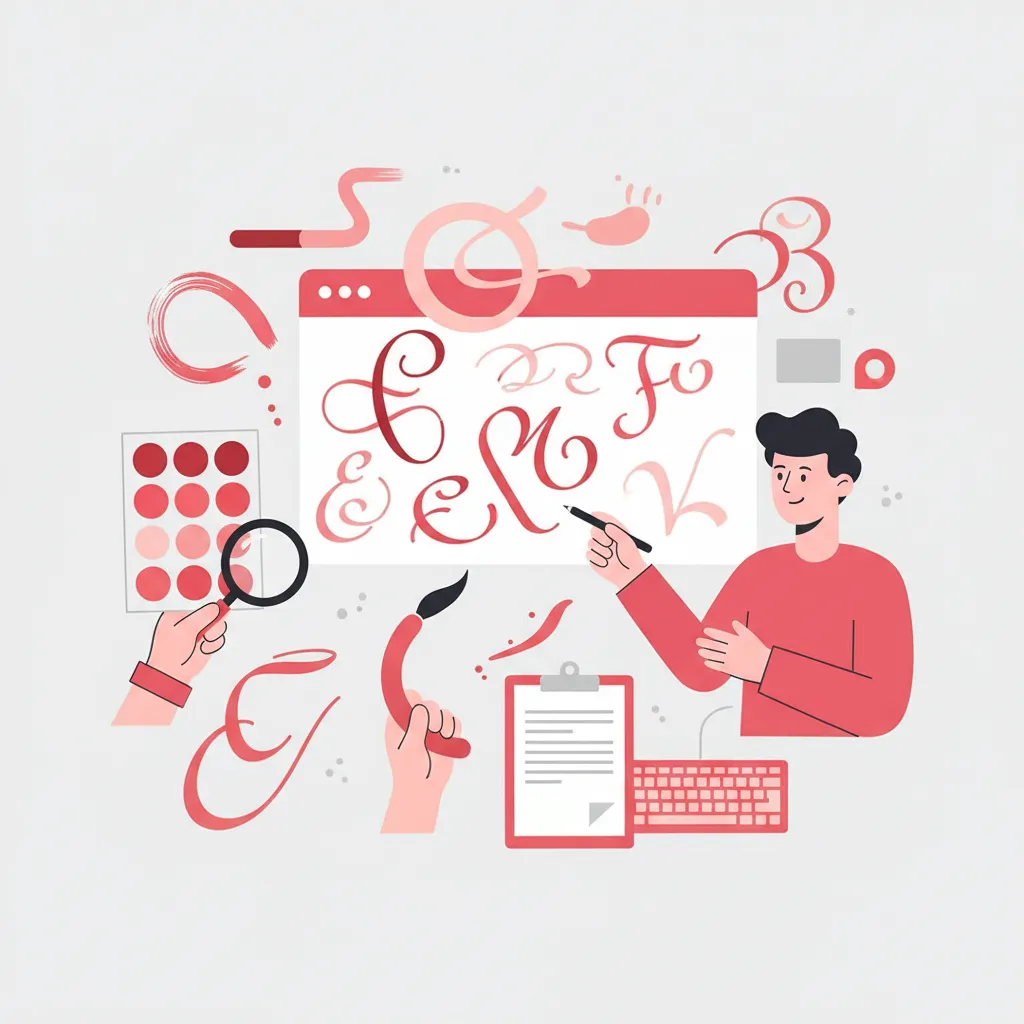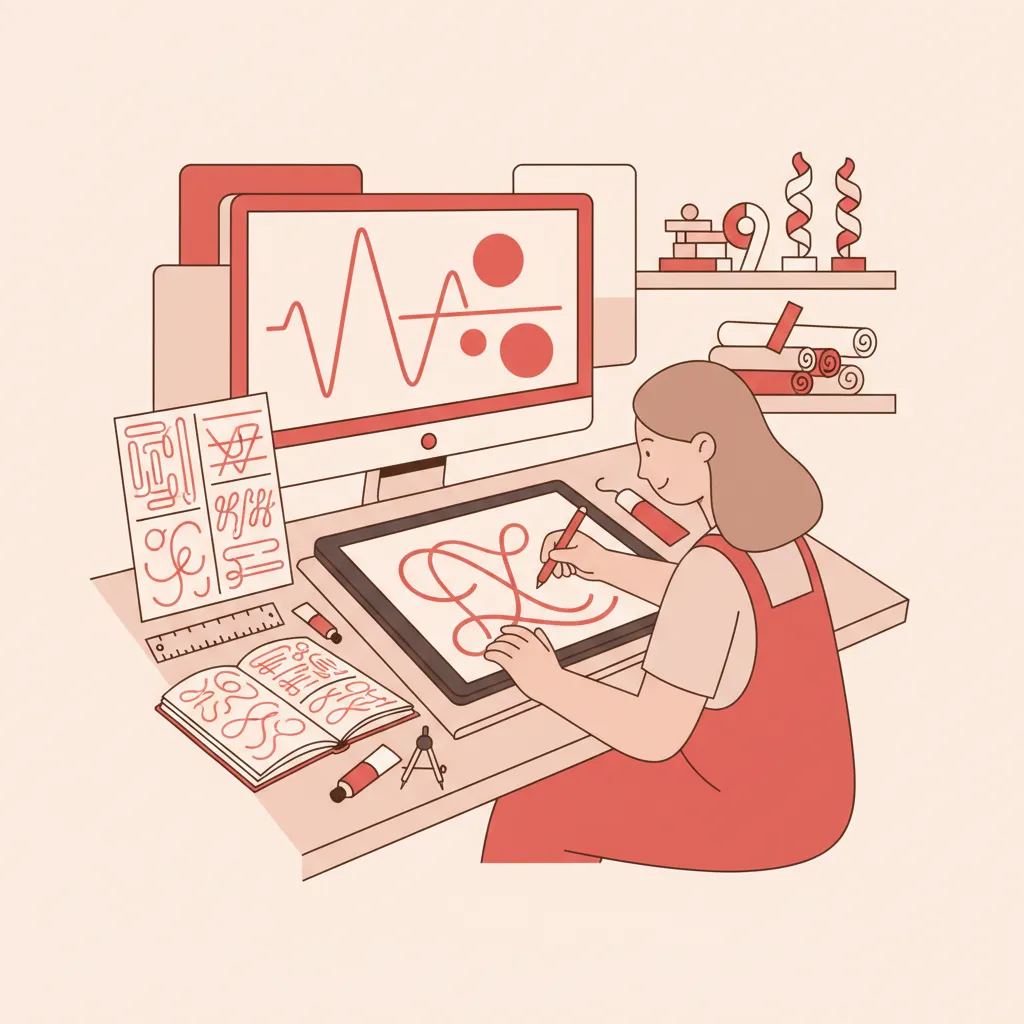
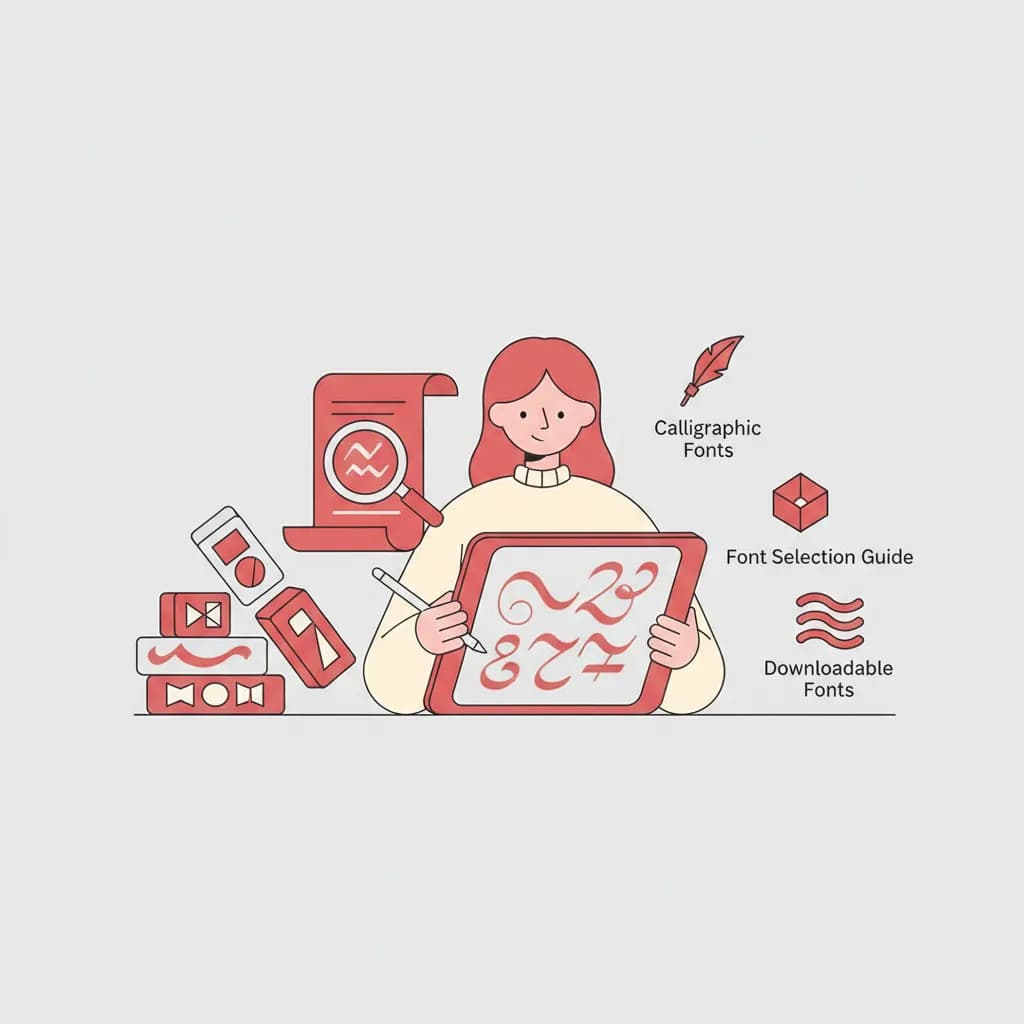
כשמדובר באותיות להורדה, הבחירה הנכונה יכולה להיות ההבדל בין עיצוב שנשכח לבין עיצוב שנחרט בזיכרון. אותיות להורדה הן קבצי פונט דיגיטליים המאפשרים למעצבים, בעלי עסקים ויוצרי תוכן להשתמש בטיפוגרפיה ייחודית בכל פרויקט – מלוגו ועד הזמנת חתונה. בשוק הדיגיטלי של 2025, מגוון הפונטים העבריים האיכותיים גדל משמעותית, אך גם הקושי לאתר את הפונט המתאים ביותר לצרכים הספציפיים שלכם. מדריך זה ילווה אתכם בתהליך המלא – מהבנת הצרכים ועד להורדה מוצלחת.
⚡ נקודות מפתח:אותיות להורדה הן קבצי פונט דיגיטליים המאפשרים שימוש בטיפוגרפיה ייחודית מעבר לפונטים המותקנים כברירת מחדל על המחשב. בעולם העיצוב המודרני, הפונטים המובנים במערכת ההפעלה – כמו Arial או David – אינם מספיקים כדי ליצור זהות ויזואלית ייחודית. אותיות להורדה מאפשרות למעצבים גרפיים, בעלי עסקים ויוצרי תוכן לבדל את עצמם ולהעביר מסר ויזואלי מדויק.
בעברית, הצורך בפונטים מגוונים הוא אפילו חריף יותר. השפה העברית כוללת 22 אותיות ייחודיות הנכתבות מימין לשמאל, ועיצוב פונט עברי מקצועי דורש הבנה עמוקה של קליגרפיה, ניקוד ואסתטיקה. כפי שמסבירים מעצבי פונטים מוכרים בעולם, עיצוב פונט עברי מקצועי שונה מהותית מעיצוב פונט לטיני ומחייב מומחיות ספציפית.
מעבר לאסתטיקה, אותיות להורדה משפיעות ישירות על חוויית המשתמש, על תפיסת המותג ועל קריאות הטקסט. בתחום ה-UX Research נמצא כי טיפוגרפיה מתאימה משפרת את שיעור הקריאה ואת הזמן שמשתמשים מבלים בדף. לכן, בחירת אותיות להורדה היא לא רק שאלה אסתטית – היא החלטה אסטרטגית.
תהליך איתור אותיות להורדה מקצועיות דורש יותר מסתם חיפוש גוגל. מעצבים מנוסים עוקבים אחר תהליך מובנה שמבטיח שהפונט שנבחר מתאים לצורך, לפלטפורמה ולרישיון המבוקש. הנה התהליך המלא:
שלב 1: הגדרת הצורך
לפני שמחפשים אותיות להורדה, חשוב להגדיר בדיוק את השימוש המיועד. האם מדובר בפונט לכותרות בולטות, לטקסט רץ ארוך, לעיצוב לוגו, או אולי לפרויקט קליגרפי? לכל שימוש מתאים סוג פונט שונה.
שלב 2: בחירת הסגנון הטיפוגרפי
פונטים עבריים מתחלקים לקטגוריות עיקריות: סריף (עם תגים בקצות האותיות), סנס-סריף (ללא תגים, נקי ומודרני), כתב יד וסגנון קליגרפי. לפרויקט מיתוג יוקרתי – סריף אלגנטי. לממשק דיגיטלי נקי – סנס-סריף. לאירוע חגיגי – כתב יד.
שלב 4: בדיקת איכות הפונט
פונט איכותי כולל תמיכה מלאה בניקוד עברי, טיפול נכון בסופיות (ך, ם, ן, ף, ץ), קרנינג מוקפד (מרווחים בין אותיות) ותמיכה בסימני פיסוק. פונטים בעברית מקצועיים גם כוללים מספר משקלים (לייט, רגיל, בולד) לגמישות עיצובית מרבית.
לא כל אותיות להורדה מתאימות לכל פרויקט. ההתאמה בין סוג הפונט לסוג הפרויקט היא מה שמבדיל עיצוב מקצועי מעיצוב חובבני. הנה מדריך התאמה מהיר לפי קטגוריות עיקריות:
סוג הפרויקט סגנון פונט מומלץ דוגמה מיתוג עסקי סנס-סריף נקי, משקלים מרובים פונט דיפלומט הזמנות חתונה קליגרפי, כתב יד, מקושט פונט רומנטיקה אתר אינטרנט סנס-סריף, תמיכת WOFF2 פונט אספרסו רשתות חברתיות בולד, דיספליי, מושך עין פונט אליאל ספרות ותוכן ארוך סריף קריא, מנוקד פונט שחריתלפרויקטי מיתוג יוקרתיים שדורשים גמישות טיפוגרפית, כדאי לבחור פונטים עם משפחת משקלים מלאה. למשל, פונט דיפלומט מציע שמונה משקלים שונים – מאקסטרה לייט ועד אקסטרה בולד – עם תמיכה דו-לשונית, מה שמאפשר עיצוב עקבי בכל פלטפורמה.
לאירועים רומנטיים כמו חתונות, אותיות להורדה בסגנון קליגרפי מוסיפות ממד רגשי לעיצוב. למשל, לעיצוב הזמנות חתונה, פונט רומנטיקה הוא פונט מקושט ומעוטר שמשדר אהבה ואלגנטיות – ומתאים במיוחד לכותרות ולפרטים מיוחדים בהזמנה. לקריאה נוספת על טיפוגרפיה לאירועים, ראו פונטים לעיצוב נירות חתונה.
לפרויקטים דיגיטליים, חשוב לבחור אותיות להורדה שנועדו לווב. Google Fonts מציעה אפשרויות עבריות בסיסיות בחינם, אך לפונטים עבריים ייחודיים ומקצועיים יותר, ספקים מתמחים כמו Lia Fonts מציעים מגוון רחב בהרבה. לפרטים על אופטימיזציית פונטים לאתרים, ראו כך תשפרו את ביצועי האתר שלכם עם פונטים אופטימליים לווב.
מניסיון עם מעצבים מקצועיים, ישנם מספר עקרונות שמבדילים בין בחירת אותיות להורדה מוצלחת לבין בחירה שמסתיימת בתסכול. הנה הצ'ק-ליסט שכדאי לעבור לפני כל הורדה:
טיפ מקצועי נוסף: כשמשלבים שתי אותיות להורדה באותו פרויקט, חשוב לוודא שהן עובדות יחד ויזואלית. גישה מקובלת היא לשלב פונט סריף לכותרות עם פונט סנס-סריף לגוף הטקסט. לדוגמה, פונט שחרית הקליגרפי לכותרת ופונט אספרסו הסנס-סריף לגוף – שילוב שיוצר ניגודיות מעניינת ועדיין נראה מאוחד.
לפרויקטים שדורשים גמישות מרבית, כדאי לבחור אותיות להורדה עם תמיכה דו-לשונית. למשל, פונט אספרסו הוא פונט סנס-סריף דו-לשוני עם שבעה משקלים, המאפשר עיצוב עקבי גם בטקסטים המשלבים עברית ואנגלית. לעיצוב שמעביר מסרים בצורה מדויקת, ראו גם עיצוב מילים בצורה שתעביר בדיוק את המסר.
⚡ נקודת מפתח:
גם מעצבים מנוסים עושים טעויות בתהליך איתור אותיות להורדה. הנה הטעויות השכיחות ביותר – וכיצד להימנע מהן:
טעות 1: הורדת אותיות להורדה ממקורות לא מאומתים
אחת הטעויות הנפוצות ביותר היא הורדת אותיות להורדה מאתרים לא מהימנים. קבצי פונט יכולים להכיל קוד זדוני, ולחלופין, הפונטים עצמם עלולים להיות גנובים ולחשוף אתכם לתביעות. תמיד הורידו מספקים מוכרים ומהימנים.
הנה שלושה רעיונות ליישום מיידי: ראשית, בחרו פרויקט קיים ובחנו האם הפונט הנוכחי מתאים לאופי שלו – לעיתים החלפת פונט אחד יכולה לשדרג עיצוב כולו. שנית, בנו ספריית אותיות להורדה מסודרת לפי קטגוריות: כותרות, טקסט רץ, אירועים ומיתוג. שלישית, נסו לשלב פונט קליגרפי אחד עם פונט סנס-סריף נקי ובחנו כיצד הניגודיות משדרגת את העיצוב. לקריאה נוספת על 12 גופנים עבריים להורדה שמשדרגים כל עיצוב, ולהכרת מגוון הפונטים הזמינים – בקרו ב-Lia Fonts ובחנו את הקטלוג המלא.